Grow Grace Floral Christian T-Shirt
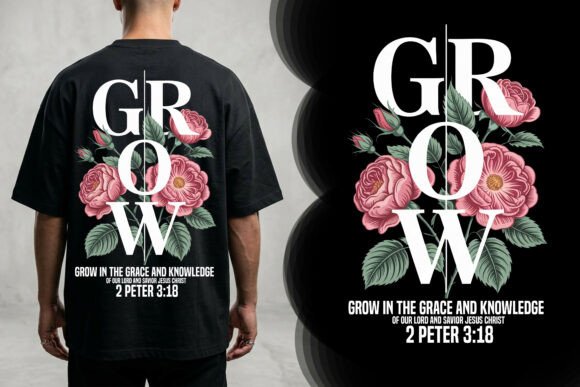
Grow Grace Floral Christian T‑Shirt – Un mélange parfait de foi et de style
Vous cherchez un vêtement chrétien qui allie élégance, spiritualité et tendance ? Le Grow Grace Floral Christian T‑Shirt est exactement ce qu’il vous faut. Ce design raffiné associe des illustrations de roses délicates à une typographie biblique percutante, offrant un message puissant tiré de 2 Pierre 3:18 : « Grow in the grace and knowledge of our Lord and Savior Jesus Christ ». Idéal pour les femmes, les événements d’église ou comme cadeau inspirant, il saura toucher le cœur des croyants tout en restant ultra‑moderne.
- Typographie biblique puissante : le texte « Grow in the grace and knowledge… » est mis en valeur par une police contemporaine qui attire le regard.
- Éléments floraux détaillés : des roses finement dessinées apportent douceur et féminité, créant un équilibre parfait entre foi et esthétique.